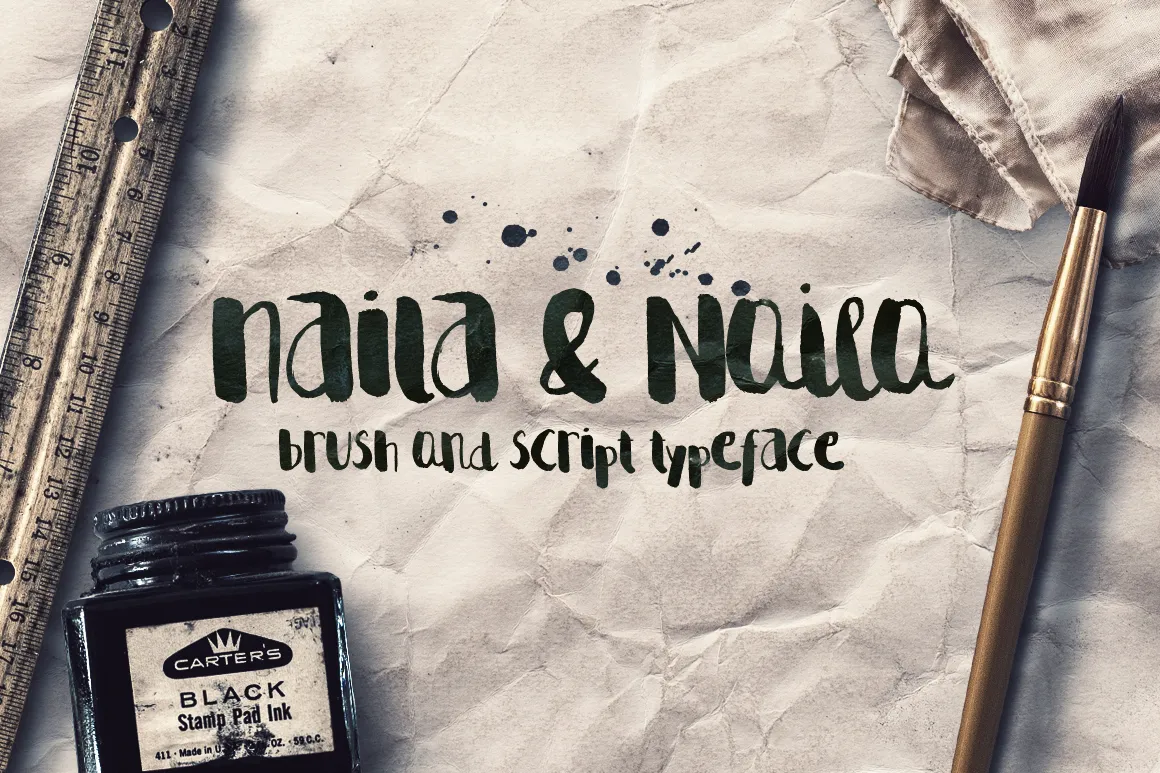
Naila Script Typeface – Download Grátis
A Naila Script Typeface é uma tipografia feita à mão que oferece uma sensação encantadora e sofisticada para qualquer projeto editorial. Ela foi criada por Hamilton, um designer dedicado, cujo profundo conhecimento e habilidade de manipular materiais físicos resultaram em linhas levemente onduladas e detalhes finos perfeitos para adicionar um toque especial a seu design. Com sua aparência fluida e elegante, essa fonte é uma ótima escolha para se destacar no campo editorial. As formas delicadamente curvadas criam texturas interessantes que podem ser usadas em qualquer tipo de projeto que exija sofisticação, desde capas de livros até cartões de aniversário personalizados. Se você está procurando por uma fonte com um toque de encanto e artefato, a Naila Script será certamente o elemento perfeito para seu próximo projeto. Ela é ideal tanto para aqueles que buscam formas fluidas quanto para os designers que valorizam texturas cuidadosamente construídas. Estamos felizes em oferecer esta demo fonte como um incentivo para adquirir a versão completa, repleta de recursos e prazos. Aqui está uma chance perfeita para experimentar o poder da Naila Script.